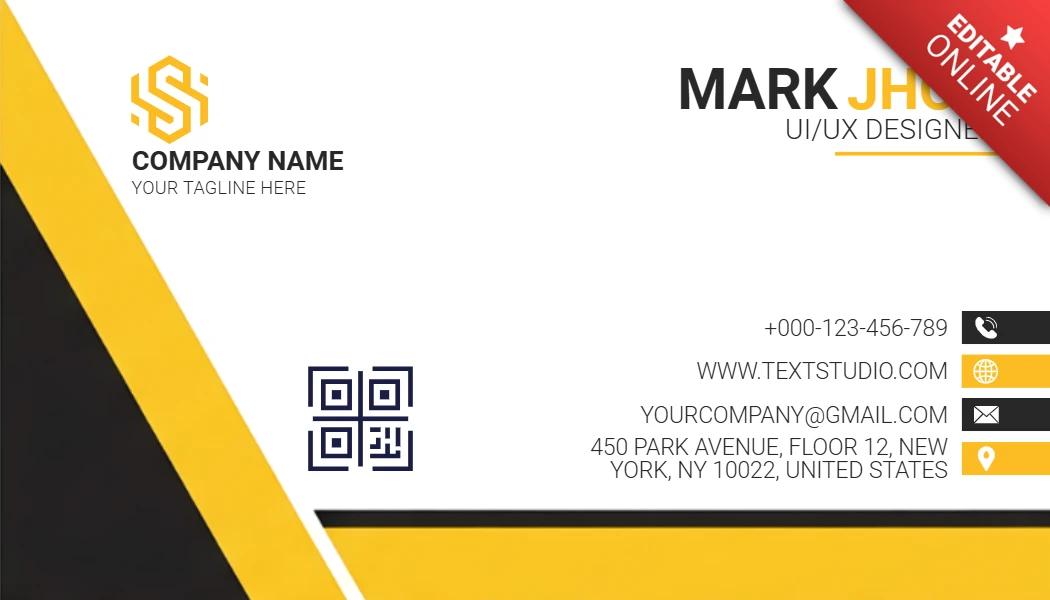
Design de carte de visite moderne thème noir et jaune avec une typographie épurée
Éditer dans Design Studio Télécharger en JPGÉlevez votre marque avec notre modèle de carte de visite moderne, présentant une typographie épurée et un thème noir et jaune frappant, parfait pour le réseautage professionnel et l'identité d'entreprise.